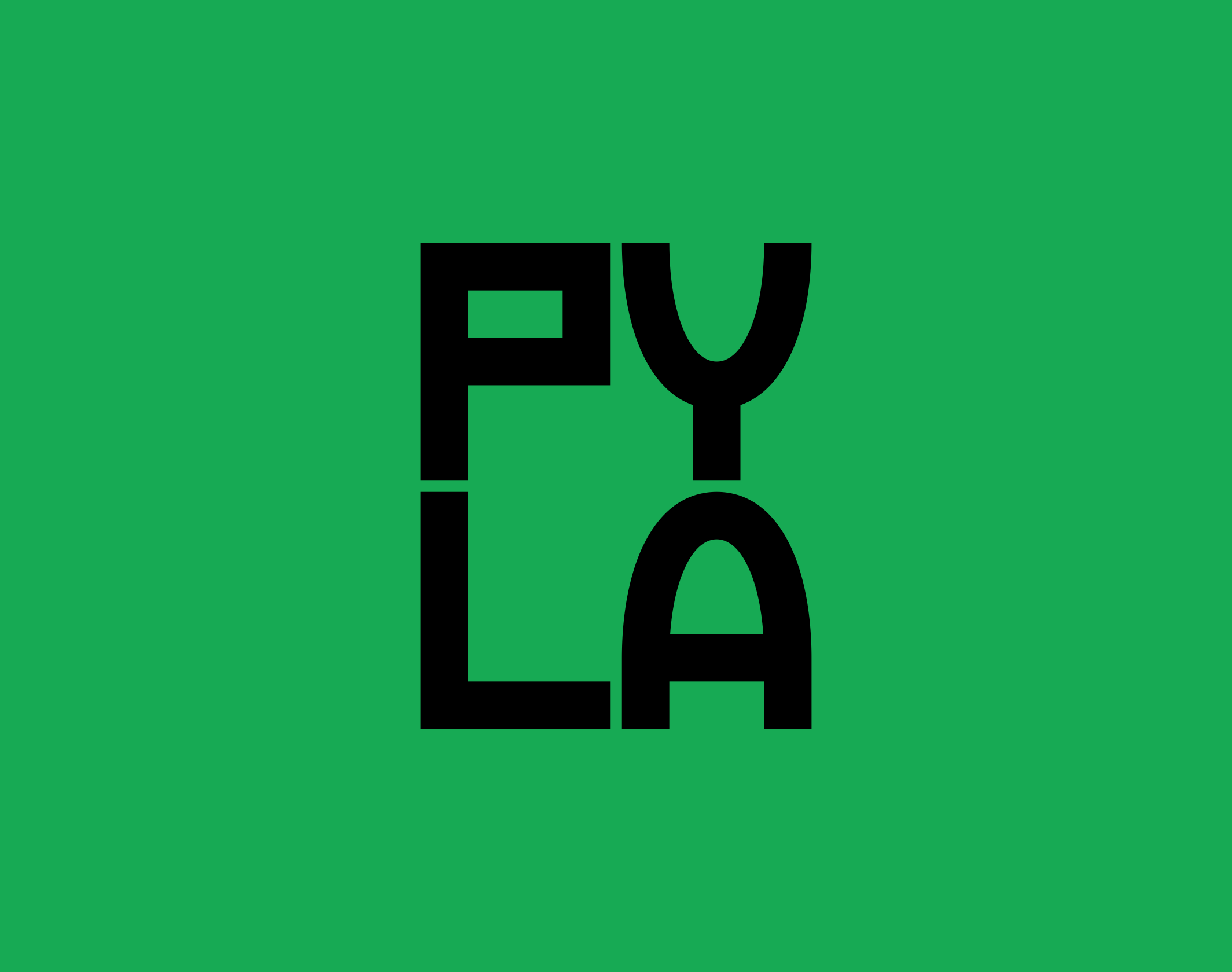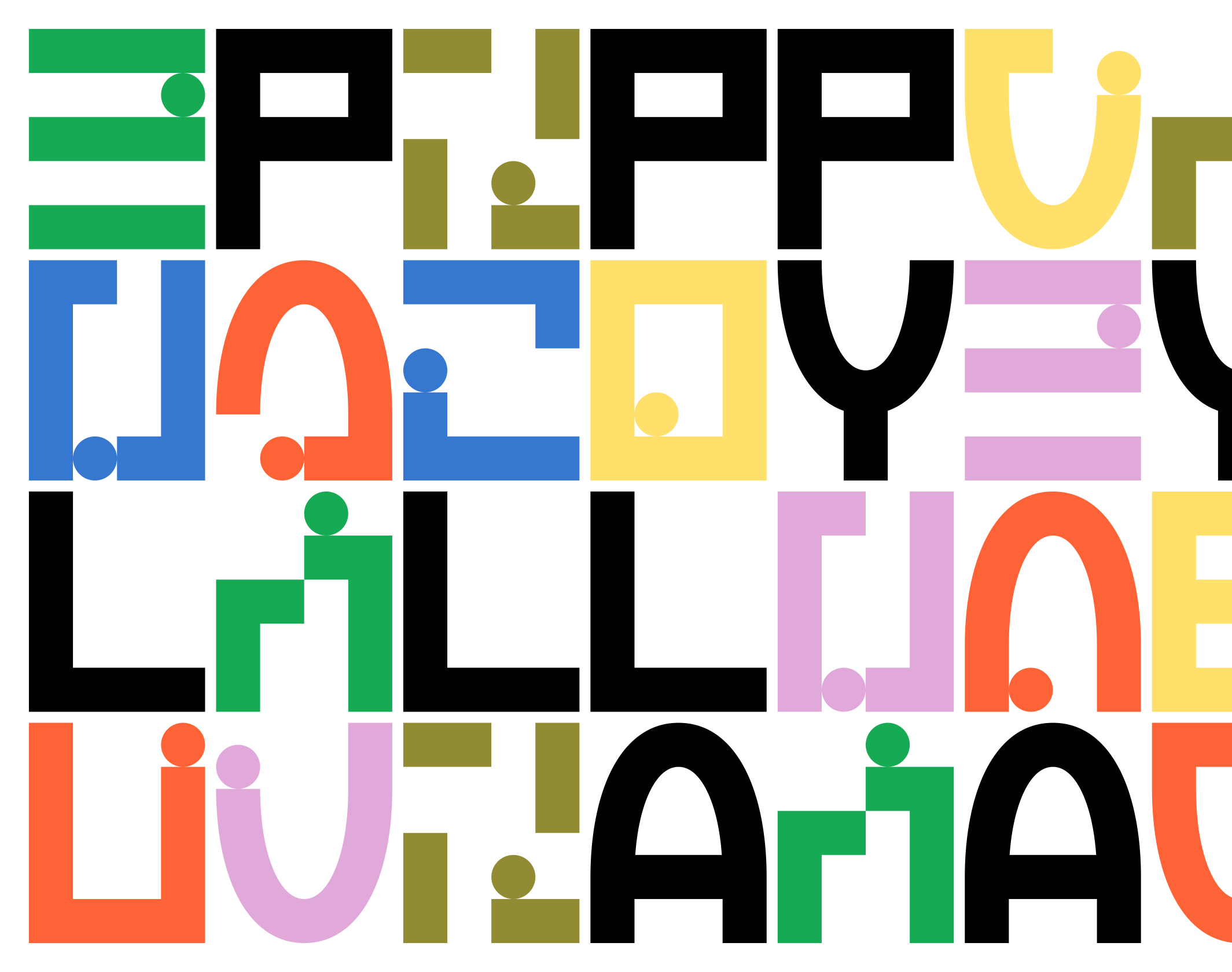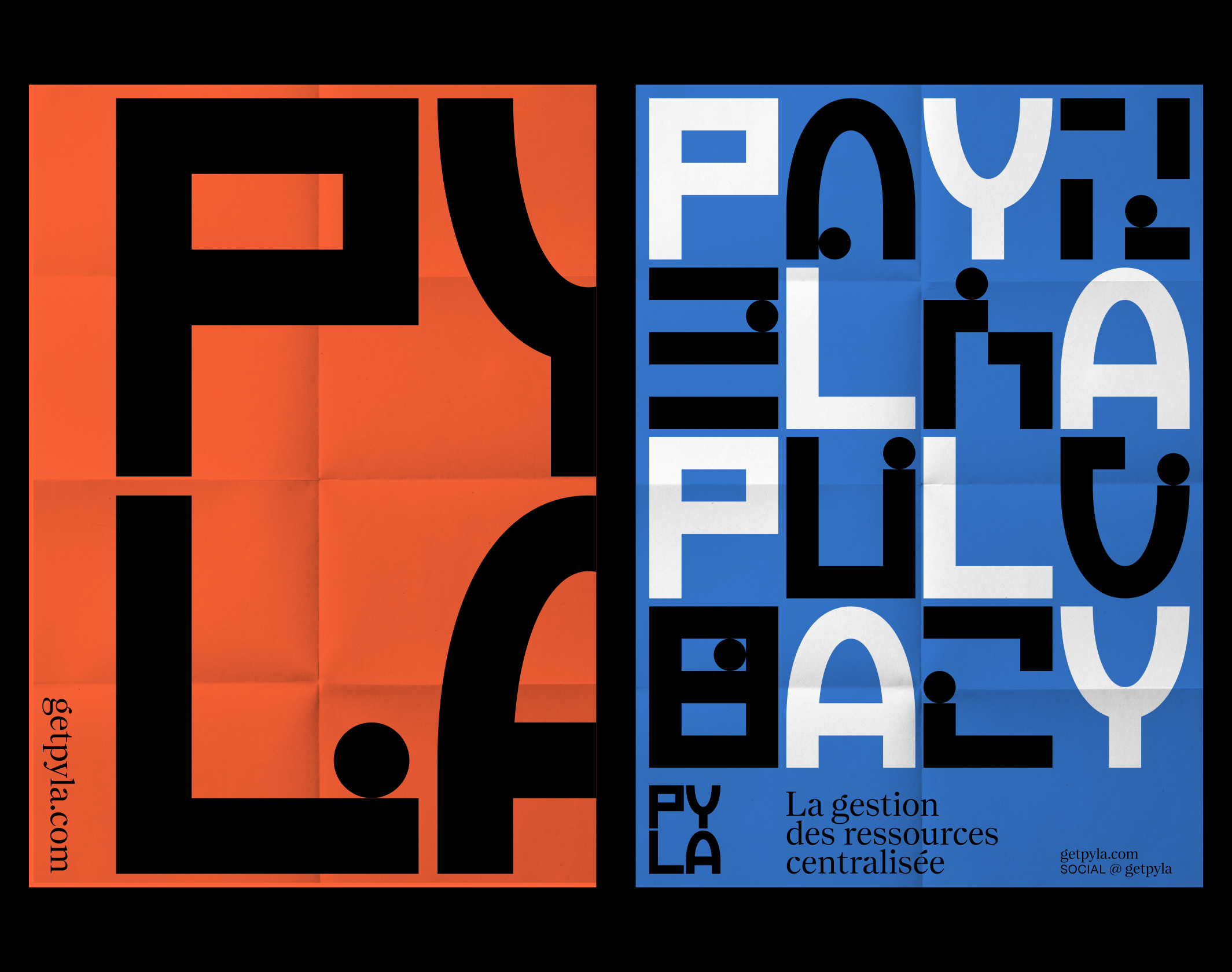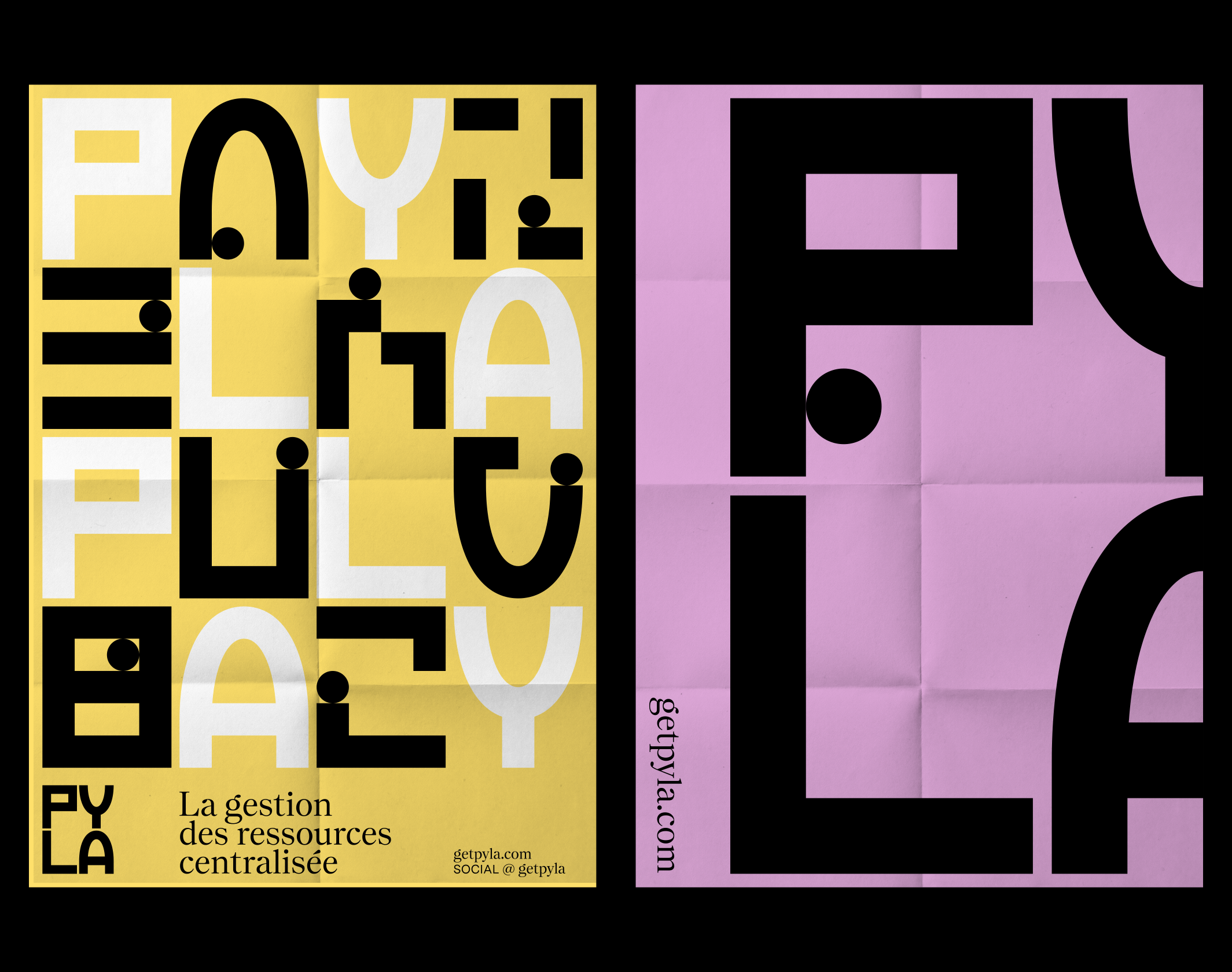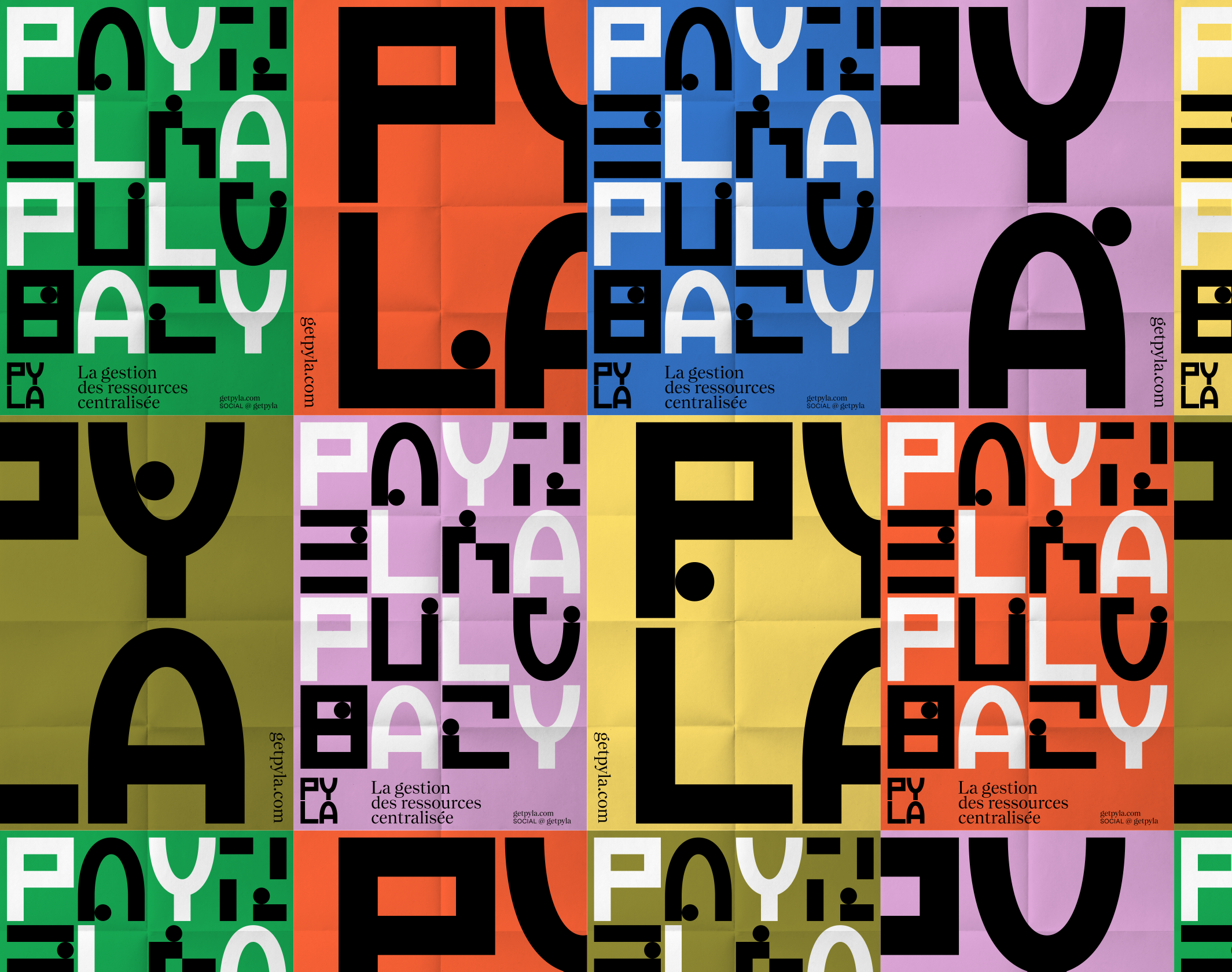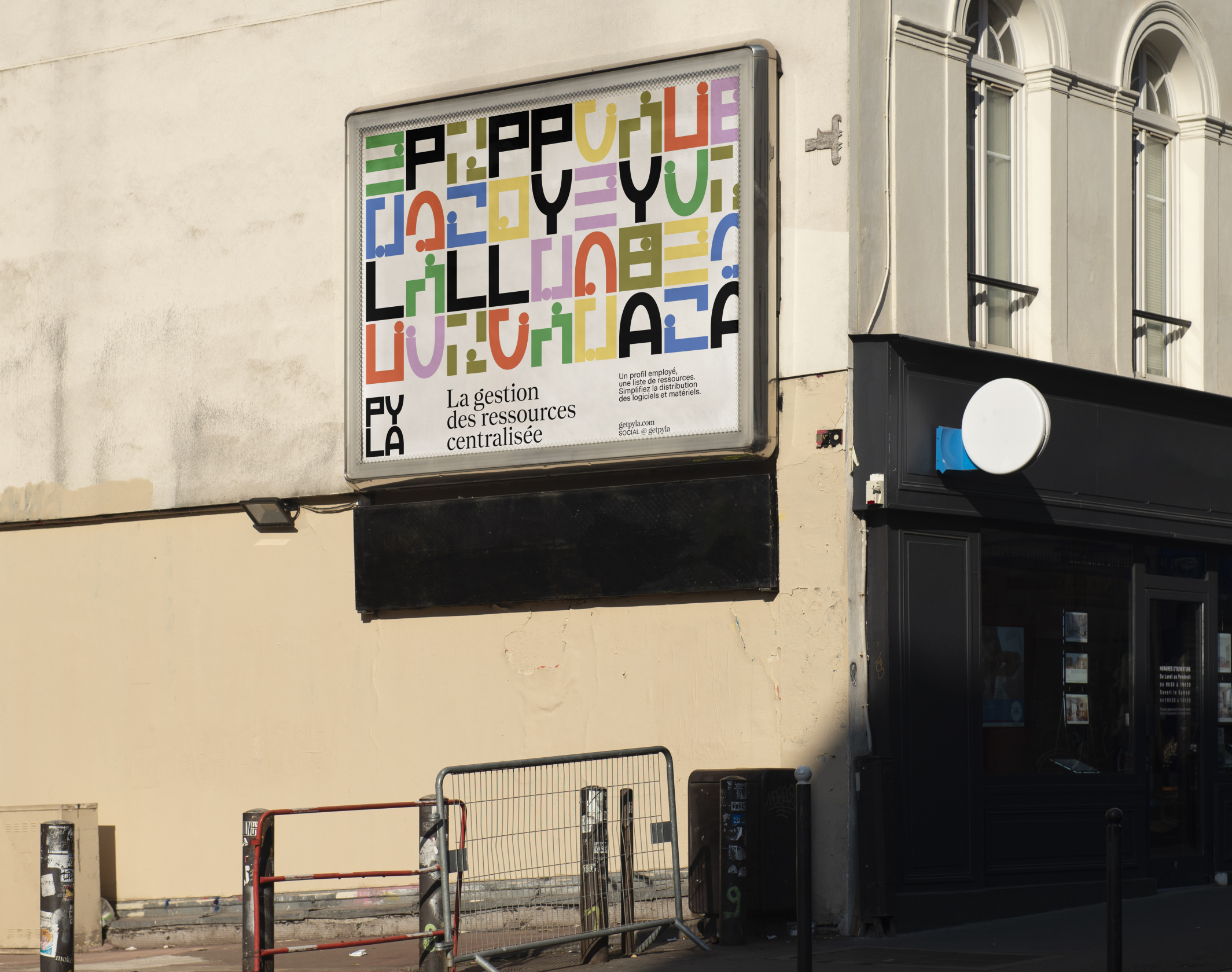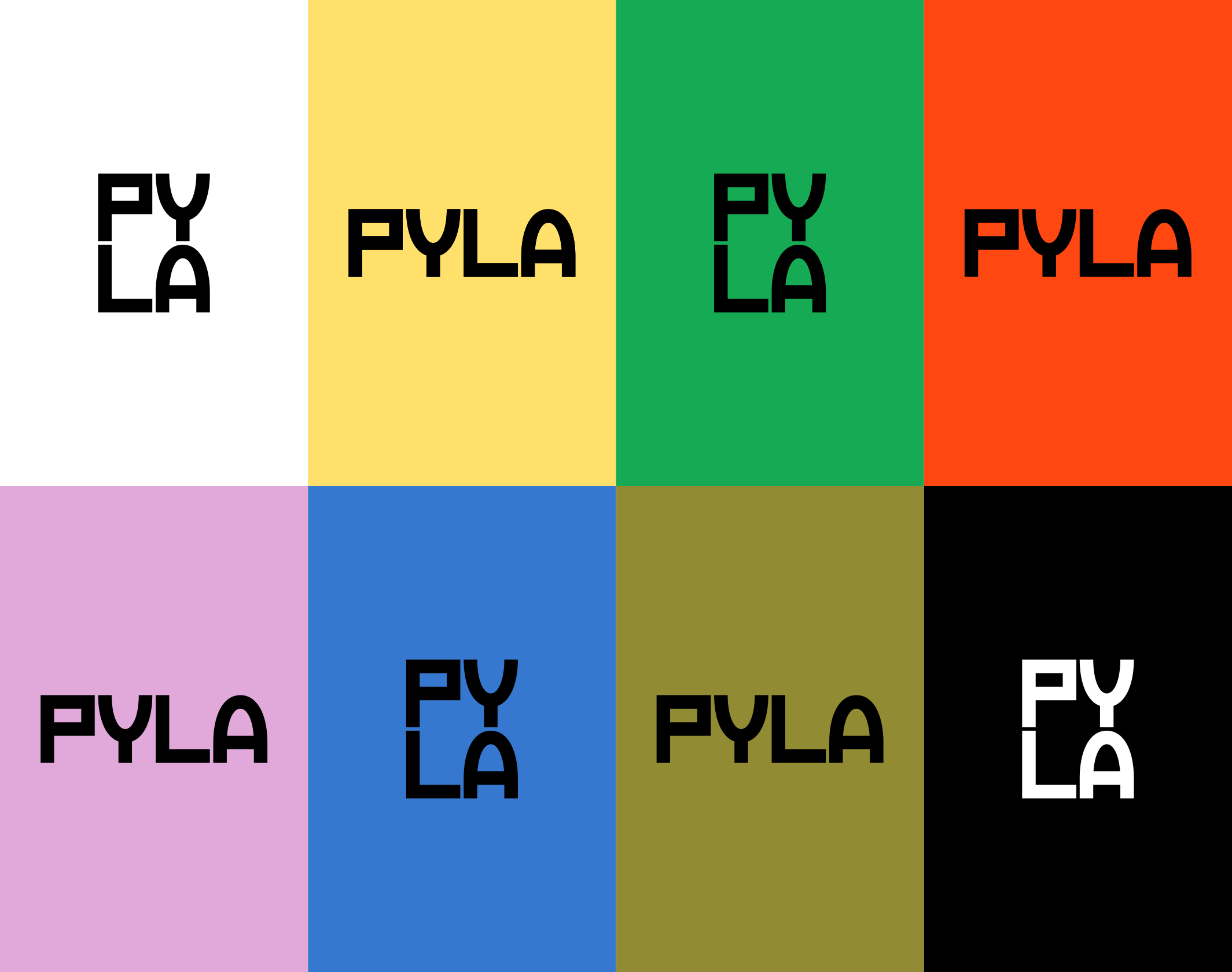
Pyla
Pyla révolutionne la gestion des ressources applicatives avec une identité visuelle dynamique et ludique, alliant efficacité et sécurité des données.
Pyla, anciennement Sweelo, est une startup créée autour d’un constat simple : un employé a besoin de plusieurs dizaines de ressources applicatives, logiciels et équipements pour être pleinement opérationnel dans son entreprise. A son arrivée et lors de son départ, les installations et manipulations engendrent des déperditions financières, de temps et d’énergie, sans compter les impacts en terme de sécurité des données. Pyla a conçu une solution qui centralise et automatise la gestion de l’ensemble de ces ressources.
Brand Brothers a développé l’identité de Pyla à l’occasion de son changement de nom, autour d’un typogramme dont le dessin des caractères résonne avec le nom. Ainsi, le P et L forment une unité autour d’un tracé rectiligne, tandis que le Y et le A, basé sur un ovale, agissent en miroir. Ces 4 caractères servent de base à un système abstrait composé de 12 formes et d’une bille, qui racontent l’empilement des applications, le flux des données et le parcours utilisateur. Une volonté manifeste de rester dans la métaphore, pour conférer à Pyla un tempérament vif et joueur au sein du monde de la data. L’environnement graphique, simple et coloré, repose sur les caractères Messina Sans et Nantes (Luzi Type, Berne, CH).